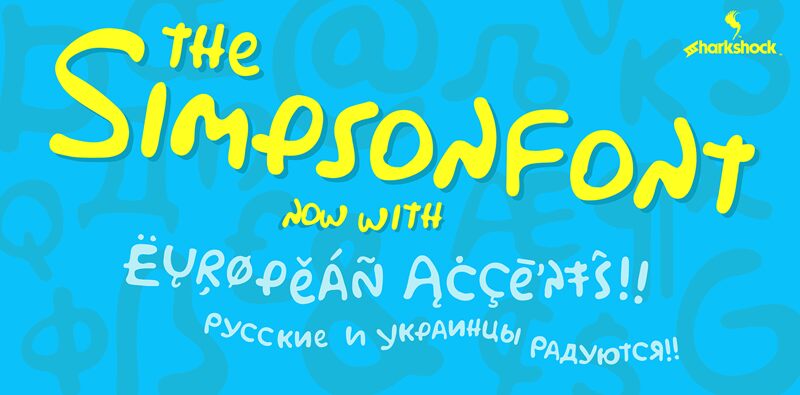
Simpsonfont, di Sharkshock Productions, è un font gratuito in stile cartoon, scritto a mano, con quella verve sciolta e rimbalzante dei lettering pop dell'era televisiva. Le lettere sono morbide e leggermente irregolari, con tratti spessi e arrotondati e un'oscillazione naturale che rende l'alfabeto giocoso invece che rigido.
È una scelta naturale per titoli di poster, inviti per feste, packaging per bambini, titoli in stile fumetto e bozzetti rapidi per loghi in cui si vuole dare un tocco animato alle parole. Essendo un font gratuito, è perfetto anche per adesivi, grafiche per merchandising e titoli brevi, specialmente quando un ritmo robusto e disegnato a mano conta più di una perfezione millimetrica.
Questo aggiornamento include glifi completamente ridisegnati, kerning, supporto per latino base/esteso, accenti europei e caratteri cirillici.
- Set di caratteri supportati: latino base/esteso, accenti europei, cirillico
- Lingue referenziate: russo, ucraino